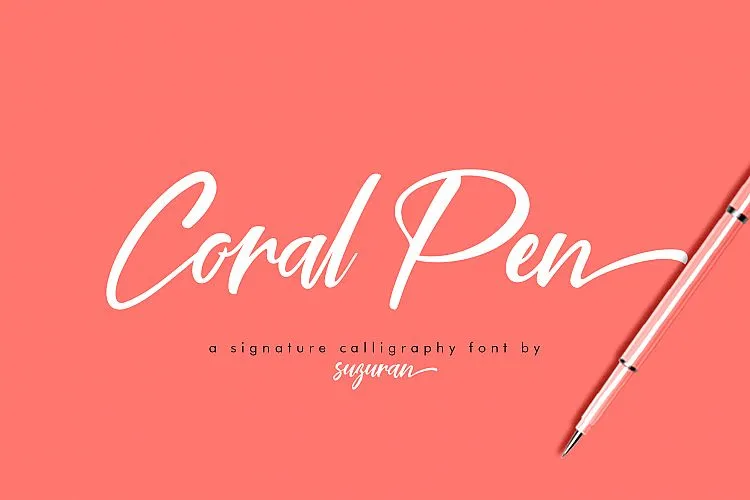
Coral Pen Script Font – Fonte Grátis
Coral Pen Script Font
Aqui está uma versão em português do Brasil para a descrição da font ‘Coral Pen Script Font’: Se você está procurando por uma fonte que destaque seu design, Coral Pen Script é definitivamente um item de desejo. Desenvolvida pelo designer Suzuran, esta fonte é como o nome sugere – uma caneta coral em estilo script. Com seu charmoso e único estilo de escrita, a Coral Pen Script é perfeita para criações digitais variadas, desde logomarcas até cardes de aniversário. Suas linhas frescas e únicas são especialmente adequadas para aplicativos como logotipos, arte em impressão, material promocional, embalagens personalizadas, convites de casamento e muito mais. A fonte Coral Pen Script traz um toque especial a qualquer projeto, tornando-o único e imediatamente reconhecível. Seja você um designer web ou gráfico, ou se está criando material promocional para sua loja online ou marca, Coral Pen Script será uma excelente adição à sua coleção de fontes. Ainda não tentou a Coral Pen Script? Vamos te convidar a dar-lhe um passeio, garantindo que suas criações brilham ainda mais.